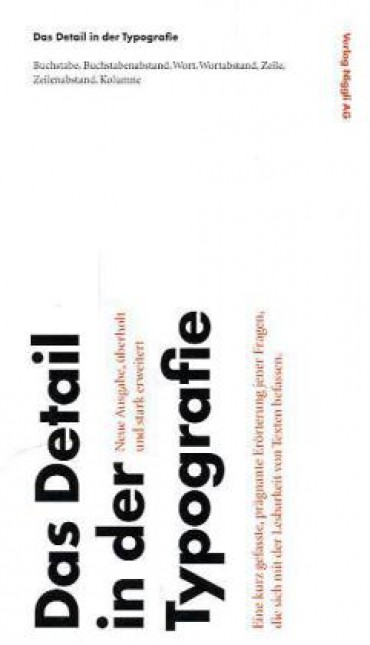
Das Detail In Der Typografie
Author: Jost Hochuli
Das Detail in der Typografie ist eine knapp gefasste Einführung in jene Fragen, die den Buchstaben, das Wort, die Zeile und den Zeilenabstand betreffen, also jene Elemente, die für die Lesbarkeit eines gedruckten Textes unerlässlich sind. Ein ansprechendes, interessantes Layout mag zwar Leserinnen und Leser erfreuen und anziehen; wenn das Detail aber nicht stimmt, wird das Lesen mühsam und die Freude ist von kurzer Dauer. Wem daran liegt, dass seine gedruckten Texte nicht nur angeschaut, sondern auch gelesen werden, der hat mit diesem Büchlein einen unverzichtbaren Leitfaden gefunden.